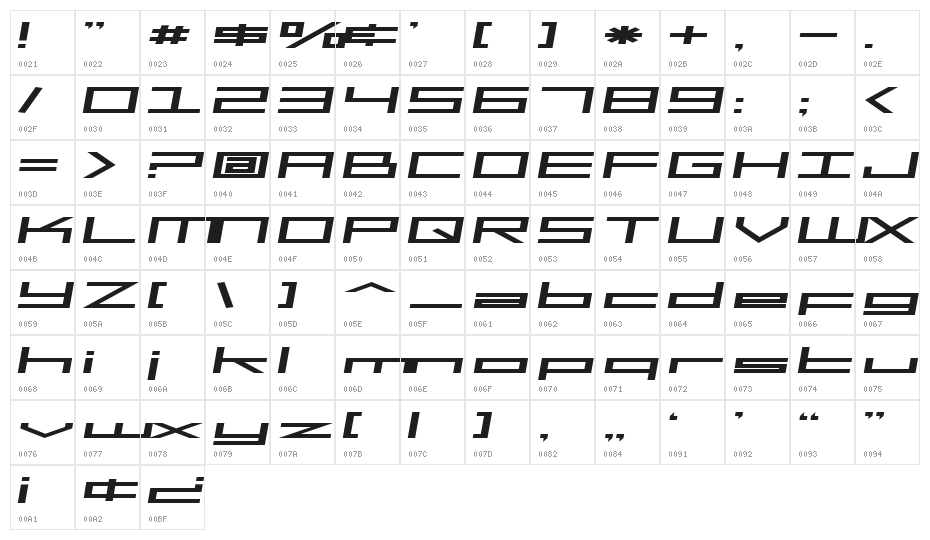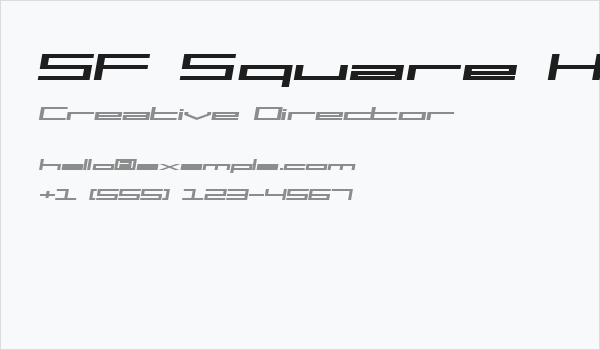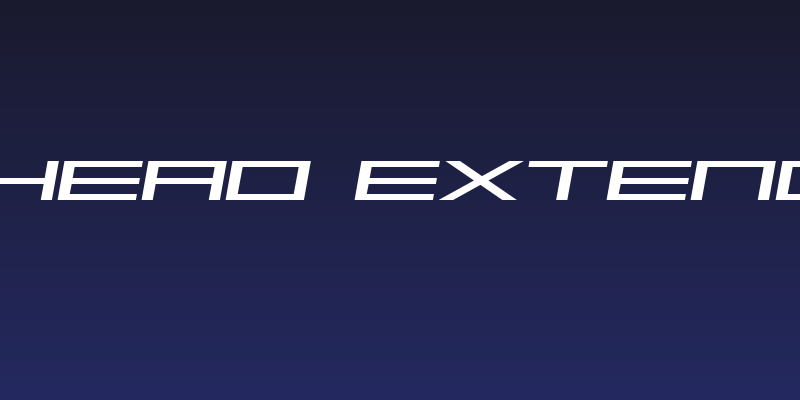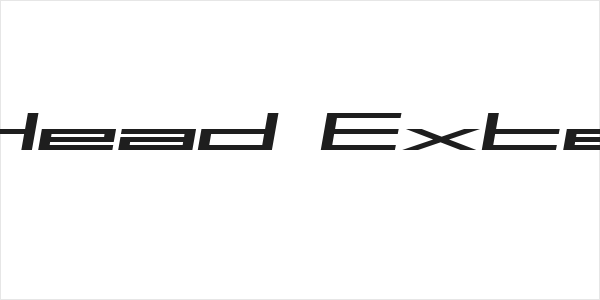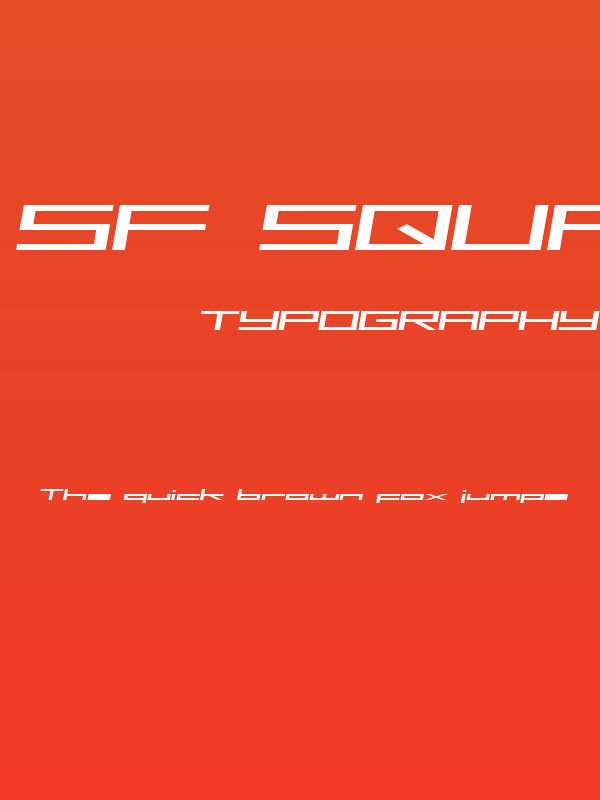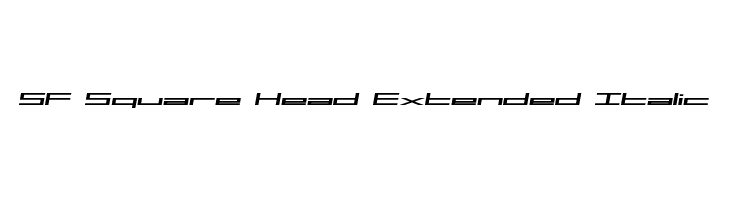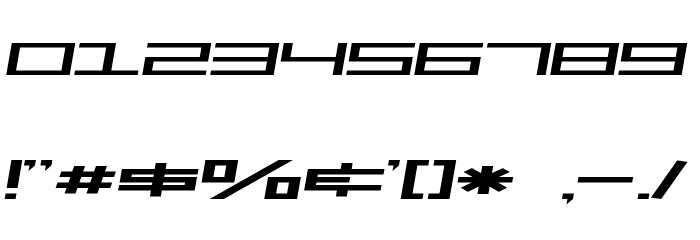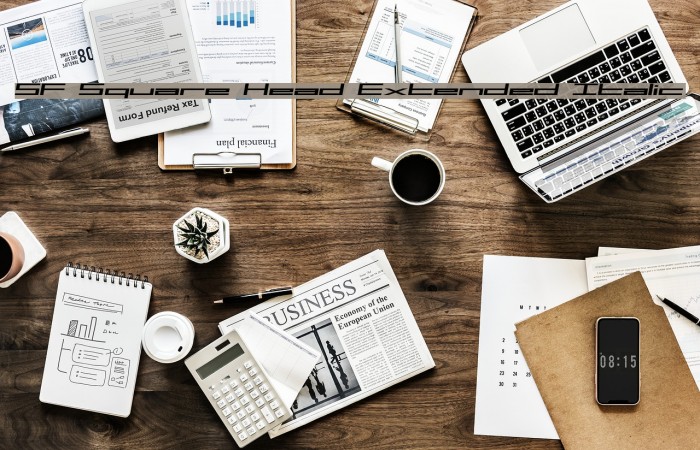
SF Square Head Extended Italic Font
Fonts by ShyFonts
| Larghezza | Expanded |
| Progetti proposti | Ideal for technology branding, sci-fi posters, video game titles, and modern web design. |
| Autore | Fonts by ShyFonts |